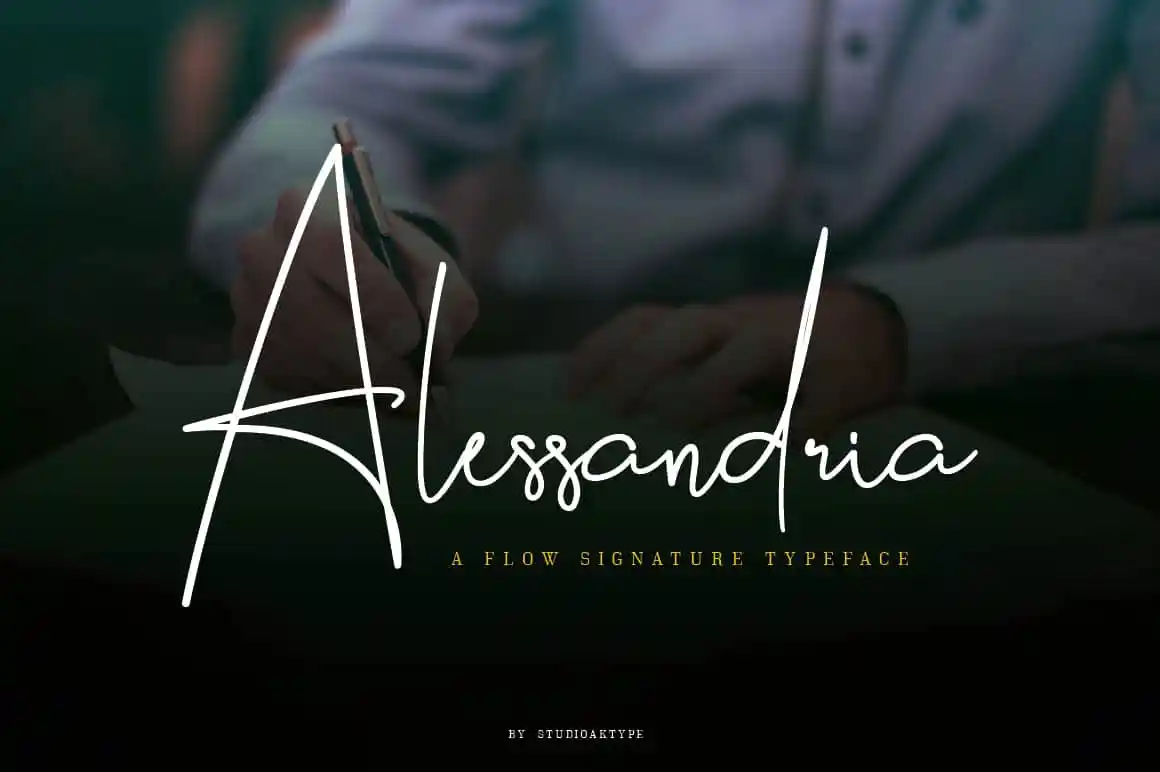
Alessandria Signature Font é uma elegante fonte de script feita para designers que valorizam um touch único e natural nas suas criações. Desenvolvida pelo designer zziplex, esta fonte se destaca por sua aparência quase autêntica e criada manualmente. Seus traços fluidos e naturais são perfeitos tanto para projetos de marca quanto para outras aplicações gráficas. Com Alessandria Font, você terá uma ferramenta ideal para trabalhar em diversos meios de impressão, como afoil embossing ou costura. Suas linhas fluídas e fluidas se adaptam perfeitamente a diferentes técnicas de impressão, permitindo que seus trabalhos estejam sempre à frente da tendência. Este é um recurso ideal para quem busca uma fonte de script que não apenas é bonita, mas também se adapta de forma natural a várias tarefas gráficas. Alessandria Signature Font oferece uma solução versátil e profissional para sua próxima criação.